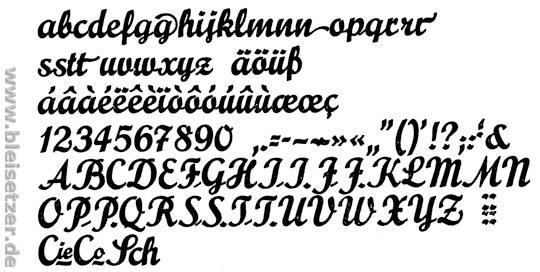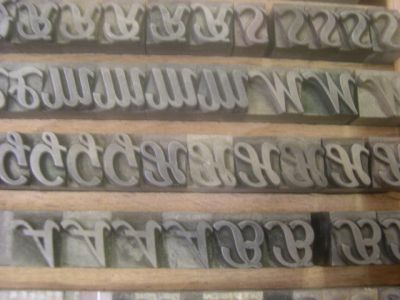
Suche alte Schreibschrift
Könnt Ihr mir sagen, was das ist?
Na, klar:
Gruppe VIII - Schreibschriften - Prägefest
Ludwig & Mayer, Frankfurt am Main
Erstguß 1926
Eduard Lautenbach
Das sind die Original-Lettern:
Was soll denn „prägefest“ bedeuten?
Das man diese Schrift zum Prägen empfohlen hat oder was … kann man nicht jede Schrift prägen, wenn diese einigermaßen stabil ist?
Das ist der Schriftname.
Die Schrift heißt „Prägefest“
Hintergrund:
Wie Du an den Bleilettern sehen kannst, hat sie kaum überstehende Grade. Und ist damit hervorragend zum Prägen einsetzbar. Normale Messing-Lettern waren auch früher schon um das ca. 20-fache teurer als Blei-Lettern.
Heute gilt:
Lettern zum Prägen sind im Idealfall aus Messing, Aluminium oder auch aus Magnesium. Bleilettern sind nur zum Drucken. Das Material ist zu weich.
Aaaber - bezogen auf eine, sagen wir, 24 p Schriftgröße:
Mit Blei-Lettern kann man bis max. 80° C auch heißprägen.
Das reicht meistens aus.
Prägt man aber z.B. mit einer Lithographia oder Künstlerschreibschrift, die weite Überhänge hat, so brechen diese beim Prägen leicht ab und beim heißprägen schmilzen die feinen Abstriche.
Das ist eine Buchbinder-Schriftenkassette mit einem Sortiment, wie es Buchbinder benötigen, hier die Umfänge:
Buchbinder brauchen viel geringere Anzahl Lettern der einzelnen Typen als Setzer. Und sie kommen bei den kleineren Schriftgraden mit der DIN-Einteilung der Brotschrift-Setzkästen nicht klar.
Also hat sich Herr Hartmann von der Bauer types, der Nachfolge-Gesellschaft der Bauerschen Gießerei in Barcelona, diese Schriftenkassetten einfallen lassen. Ein paar Spatien dabei (für die Wortzwischenräume) und ein paar Regletten (für die Zeilenabstände) und schon hat man eine handliche Stapelbox für z.B. 175,- Euro mit einer 20 p Bernhard Schönschrift kräftig.
Christoph
ps: Ich hoffe, das ist keine allzu bescheuerte Frage ... es ist ja auch schon nach 0 Uhr
23,56 mm - Deutsche Schrifthöhe
23,32 mm - 0,918 Inches - anglo-amerikanische Schrifthöhe
Die Lettern der Buchbinder sind normalerweise aus Messing oder Aluminium auf Flachkegel gegossen und geschätzt 4 mm hoch.